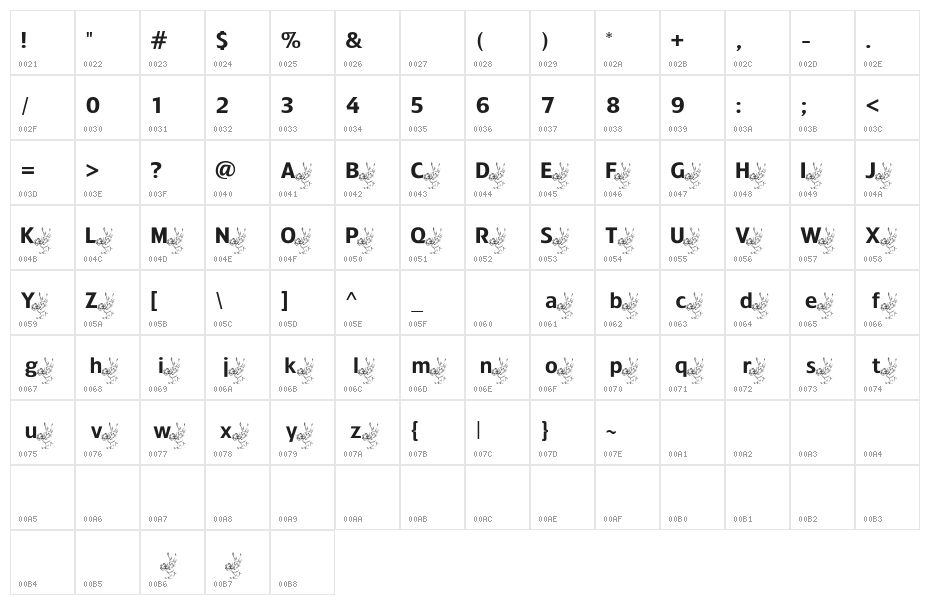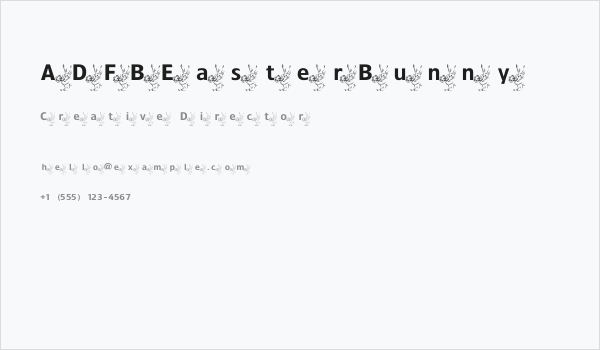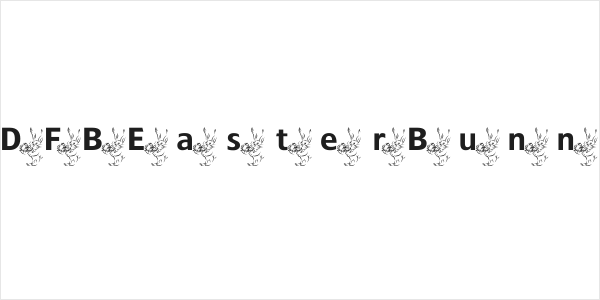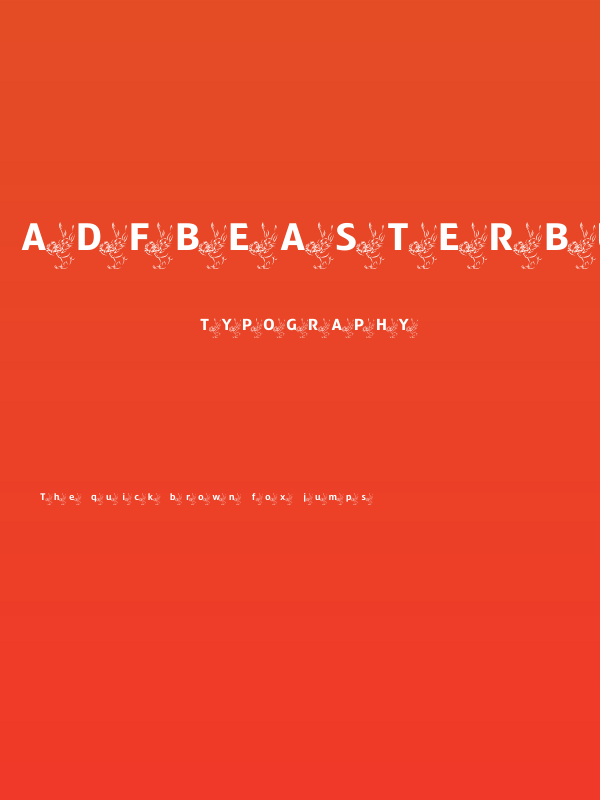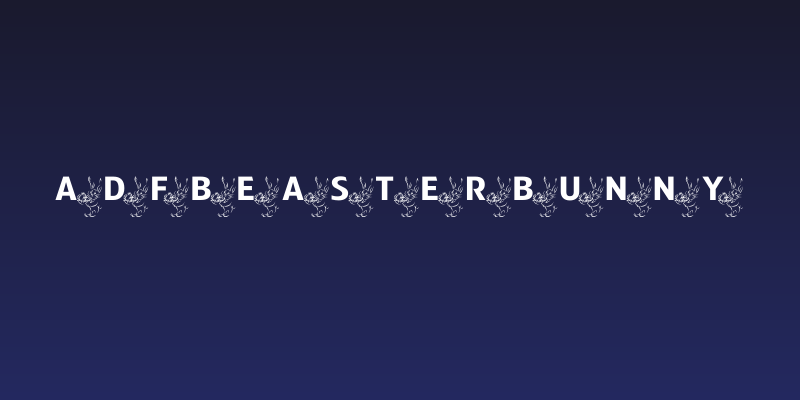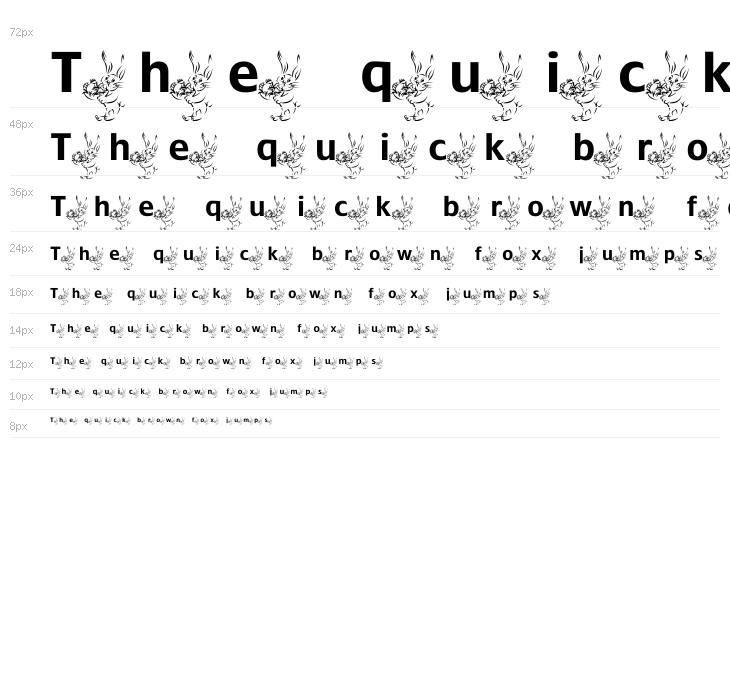
ADFBEasterBunny Font
Perry Mason
| Caso d'uso | Headlines, Logos, Invitations |
| Progetti proposti | Ideal for Easter-themed invitations, children's books, festive greeting cards, and playful branding materials. |
| Autore | Perry Mason |